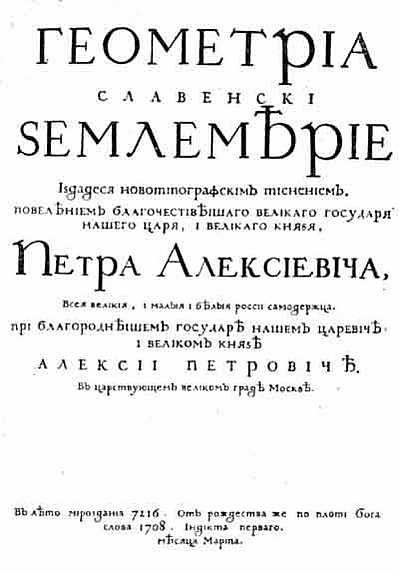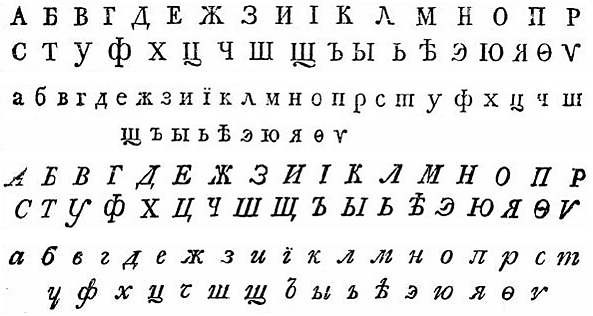
Гражданский шрифт
Гражда́нский шрифт (амстердамская азбука[1]; гражданская азбука[2] или «гражданка»[3]) — шрифт, введённый в России Петром I в 1708 году для печати светских изданий в результате первой реформы русского алфавита. В результате реформы изменился состав азбуки и упростились начертания букв, внешний вид которых был приближен к древнеримскому («латинизация» кириллицы).
Возможно, что образцом для подражания в делах книгопечатания и форме шрифта был официальный королевский шрифт, созданный в 1692 году французским королём Людовиком XIV[4] на основе романского[5].
В XVII веке полуустав, перейдя в делопроизводство, преобразуется в гражданское письмо, а его скоропись — в курсивный вариант. Предпосылкой для создания гражданского шрифта стала мода на латиницу, которая распространилась в среде образованных русских людей в 1680—1690-х годах[6]. Гражданский шрифт стал компромиссом между сторонниками традиций и теми, кто стремился к максимально полному заимствованию западной культуры.
Петровская реформа русского типографского шрифта была проведена в 1708—1710 годах. Её целью было приблизить облик русской книги и иных печатных изданий к тому, как выглядели западноевропейские издания того времени, резко отличавшиеся от типично средневековых по виду русских изданий, которые набирались церковнославянским шрифтом — полууставом. В январе 1707 года по эскизам, предположительно выполненным лично Петром I, чертёжник и рисовальщик Куленбах, состоявший при штабе армии, сделал рисунки тридцати двух строчных букв русского алфавита, а также четырёх прописных букв (А, Д, Е, Т). Полный комплект шрифтовых знаков в трёх размерах по рисункам Куленбаха был заказан в Амстердаме в типографии белорусского мастера Ильи Копиевича; одновременно шрифты по этим рисункам были заказаны в Москве, на Печатном дворе.
Как явствует из писем Петра, в июне 1707 года им были получены из Амстердама пробы шрифта среднего размера, а в сентябре — оттиски пробного набора шрифтами крупного и мелкого размера. В Голландии был приобретён печатный станок и другое типографское оборудование, а также наняты квалифицированные мастера-типографы для работы в России и обучения русских специалистов.
К концу 1707 года трое приглашённых голландских типографов (словолитец, наборщик и печатник), вместе со шрифтом, типографским станком и другими принадлежностями уже добрались до Москвы и приступили к работе. 1 января 1708 года Пётр подписал указ: «…присланным Галанския земли, города Амстердама, книжного печатного дела мастеровым людем… теми азбуками напечатать книгу Геометрию на руском языке… и иныя гражданския книги печатать темиж новыми азбуками…». Первая книга, набранная новым шрифтом, «Геометриа славенски землемерие» (учебник геометрии), была напечатана в марте 1708 года. За ней последовали другие.
Приближённый по графике к древнеримскому, новый шрифт был задуман для упрощения типографского набора на печатных станках, изготовленных в Западной Европе. Новый — гражданский — шрифт был предназначен для печати светских изданий: официальных публикаций и периодики, технической, военной, научной, учебной и художественной литературы. Помимо введения нового рисунка букв, подвергся пересмотру и состав алфавита: исключены надстрочные знаки и некоторые дублетные буквы полуустава, узаконена буква Э, утверждены европейские (арабские) цифры вместо буквенных обозначений чисел, упорядочена пунктуация и применение прописных литер в наборе. Применение полуустава было ограничено сферой богослужебной литературы. Иногда петровской реформе приписывают также введение букв У и Я, но это не вполне верно: речь может идти лишь об объявлении основным одного из начертаний, применявшихся и ранее. Так, было введено Я вместо Ѧ (малого юса).
Состав русской азбуки и её графика продолжали изменяться и позже. Алфавит устоялся к середине XVIII века и держался в таком виде вплоть до реформ 1917—1918 годов, начертание же букв вполне совпало с нынешним в середине XIX века. По образцу русского гражданского шрифта и с использованием тех же начертаний букв (с необходимыми изменениями) была в XVIII—XIX веках реорганизована письменность и других народов, использовавших кириллицу (сербская, болгарская, румынская[7]).
Курсивный вариант типографского гражданского шрифта применяется с 1734 года (впервые — в газете «Санкт-Петербургские ведомости»); он восходит к гравированному курсиву, применявшемуся уже веком ранее. Начертания типографского курсива первоначально были близки к рукописным, но со временем изменялись под влиянием прямого шрифта. В результате в нынешнем курсиве кириллицы прописные буквы по построению обычно тождественны с буквами прямого шрифта и отличаются лишь наклоном; в некоторых же гарнитурах — прежде всего рубленых — строго говоря, вообще нет курсива, а лишь наклонный шрифт.
Рукописный вариант гражданского шрифта («гражданское письмо») развивается последним — лишь во второй половине XVIII века. Ранее использовалась скоропись старого московского образца.
Гражданский шрифт до Петра I
Начертания гражданского шрифта возникли ещё в допетровское время. Общеизвестная генетическая связь кириллицы с греческим письмом издавна приводила к тому, что в декоративных целях кириллические надписи иногда делались шрифтами, начертание которых повторяло прописные греческие буквы (с соответствующей стилизацией тех славянских букв, которым в греческом не было аналогов).
Впервые реформу по упрощению и «латинизации» кириллицы произвёл ещё белорусский и восточнославянский первопечатник Франциск Скорина, который в своих пражских и виленских изданиях использовал новое, более лаконичное написание, отказался от надстрочных букв и чрезмерных сокращений, минимизировал использование сложных греческих букв «пси», «кси», «ижица» и пр., начал достаточно системно использовать близкую к современной пунктуацию и написание большой буквы. В дальнейшем этот шрифт активно использовали белорусские типографы-протестанты Василий Тяпинский в Заславле или Тяпине и Симон Будный в Несвиже. Интенсивное использование данного шрифта протестантами вызвало настороженное отношение к нему православных типографий, в результате чего позднейшие белорусские типографии ещё долго использовали менее удобную, но привычную и древнюю кириллицу. Примеры использования подобного шрифта лишь изредка встречаются в гравюрах белорусских и украинских изданий XVII века[8], а также в гравированных шрифтах заголовков. Возрождение шрифта произошло благодаря белорусскому типографу и просветителю Илье Копиевичу, который в 1700—1706 гг. (ещё до начала печати гражданским шрифтом в России) по заказу Петра I и для продажи на российском рынке издал в Амстердаме и Данциге около 25 книг. Шрифт его изданий был крайне близок к тому, который в дальнейшем был принят российским императором. Пётр I, собственно говоря, лишь упорядочил и узаконил эту практику.
По сведениям «Русского энциклопедического словаря»[9] и «Всероссийского „словаря-толкователя“»[10], «гражданские буквы… впервые употреблены в печати Петром Могилою, окончательно введены императором Петром I в 1708 г.»